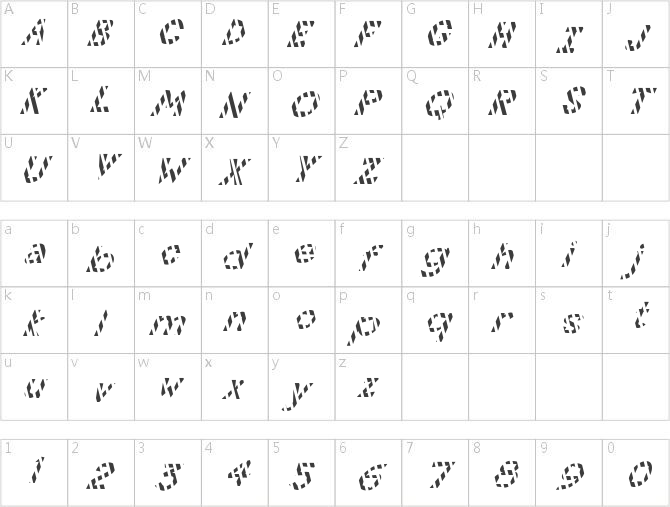
FZ JAZZY 7 STRIPED ITALIC 詳情頁
FZ JAZZY 7 STRIPED ITALIC字體字庫是一款讓人賞心悅目、百看不厭的英文字體,適合各類廣告和產(chǎn)品包裝設(shè)計(jì)應(yīng)用,字體大小0.05MB,格式為ttf字體,上傳用戶是浪跡天涯,作者/版權(quán)方為未知